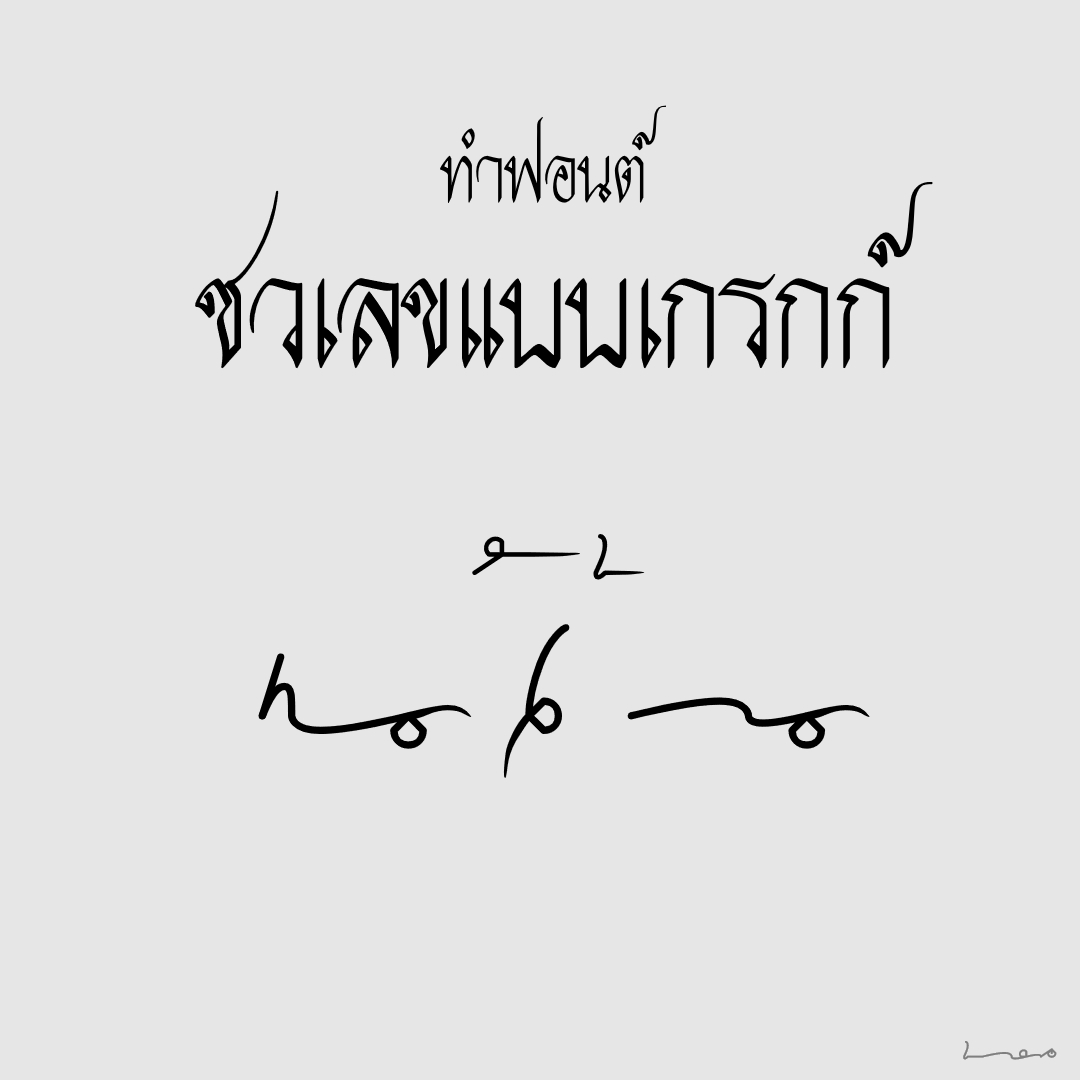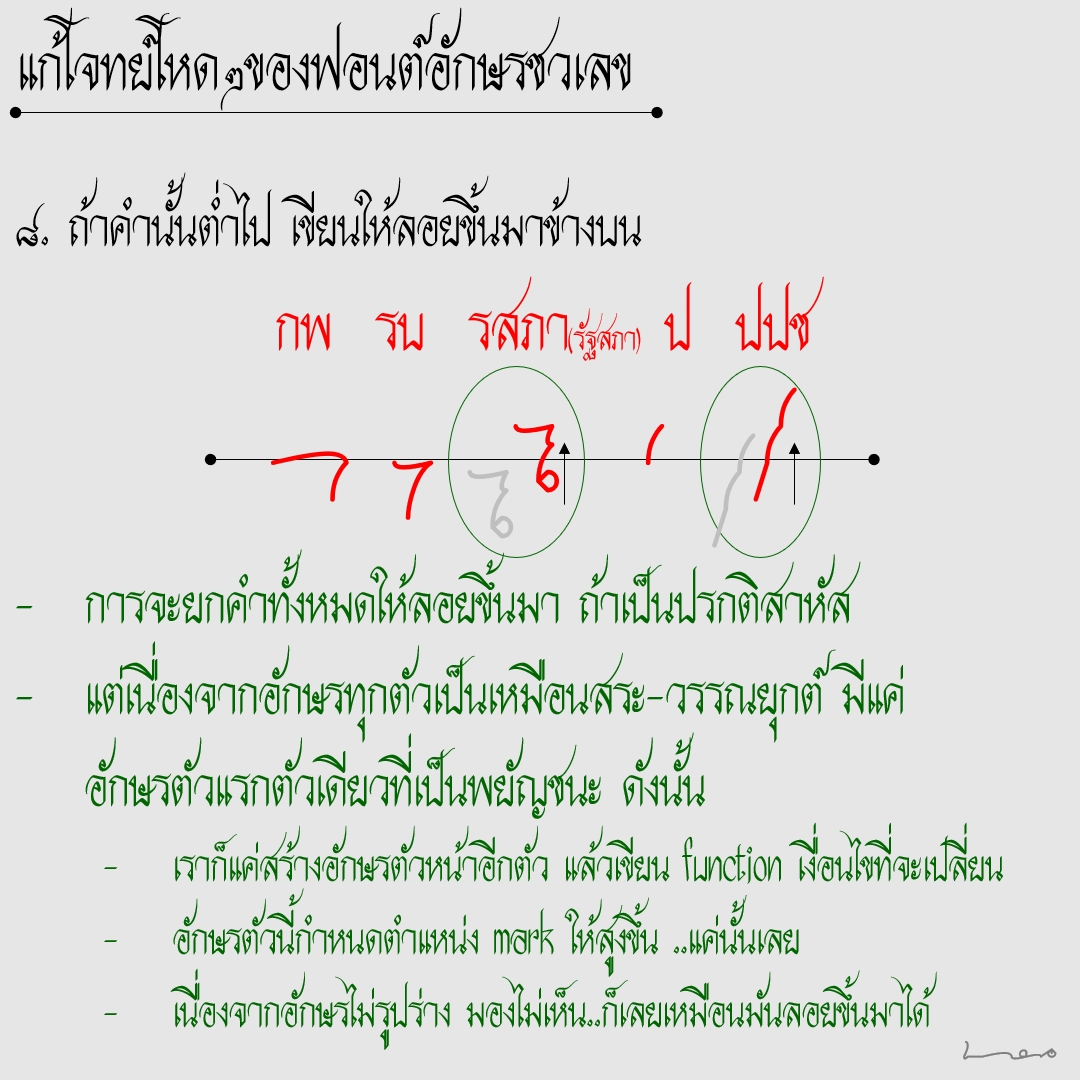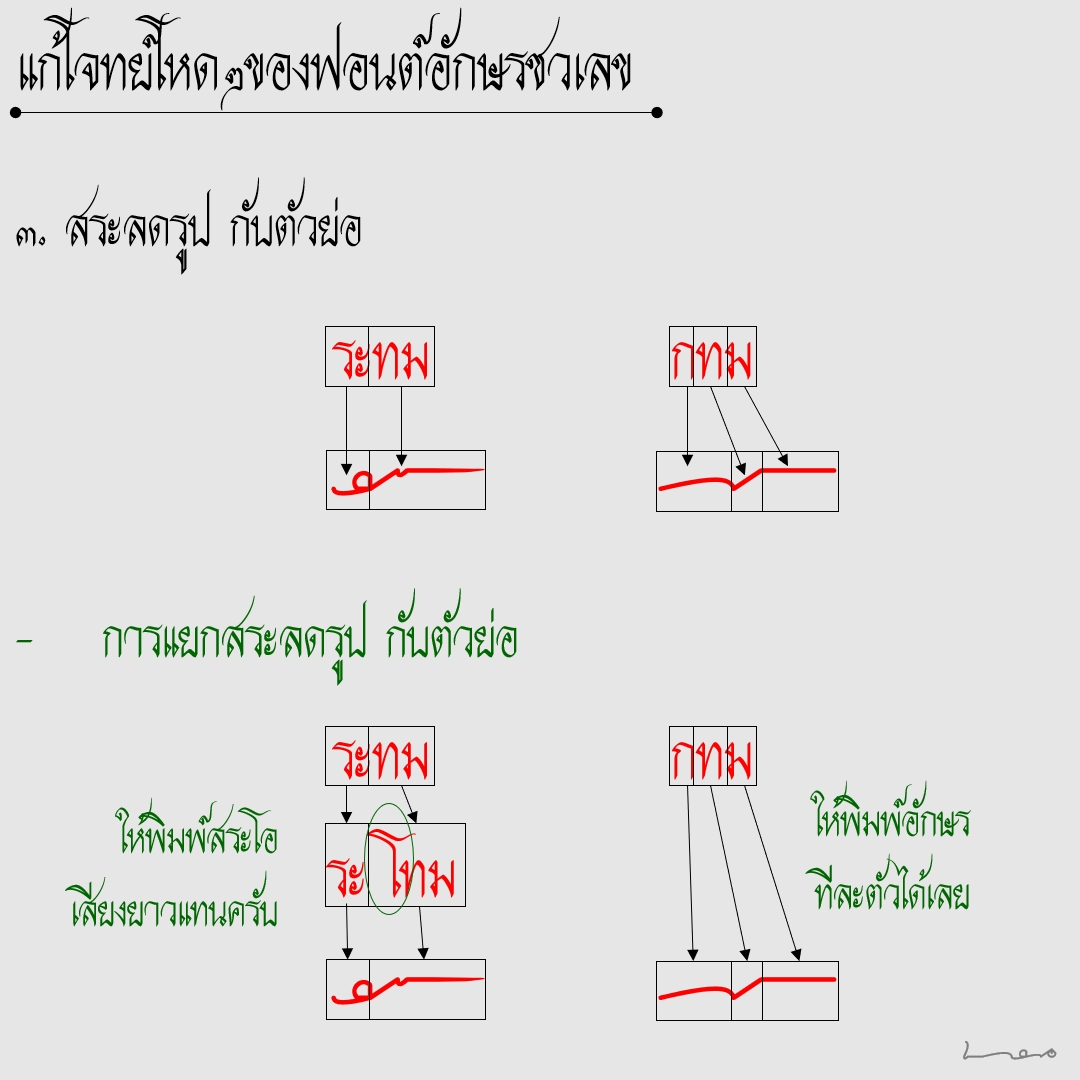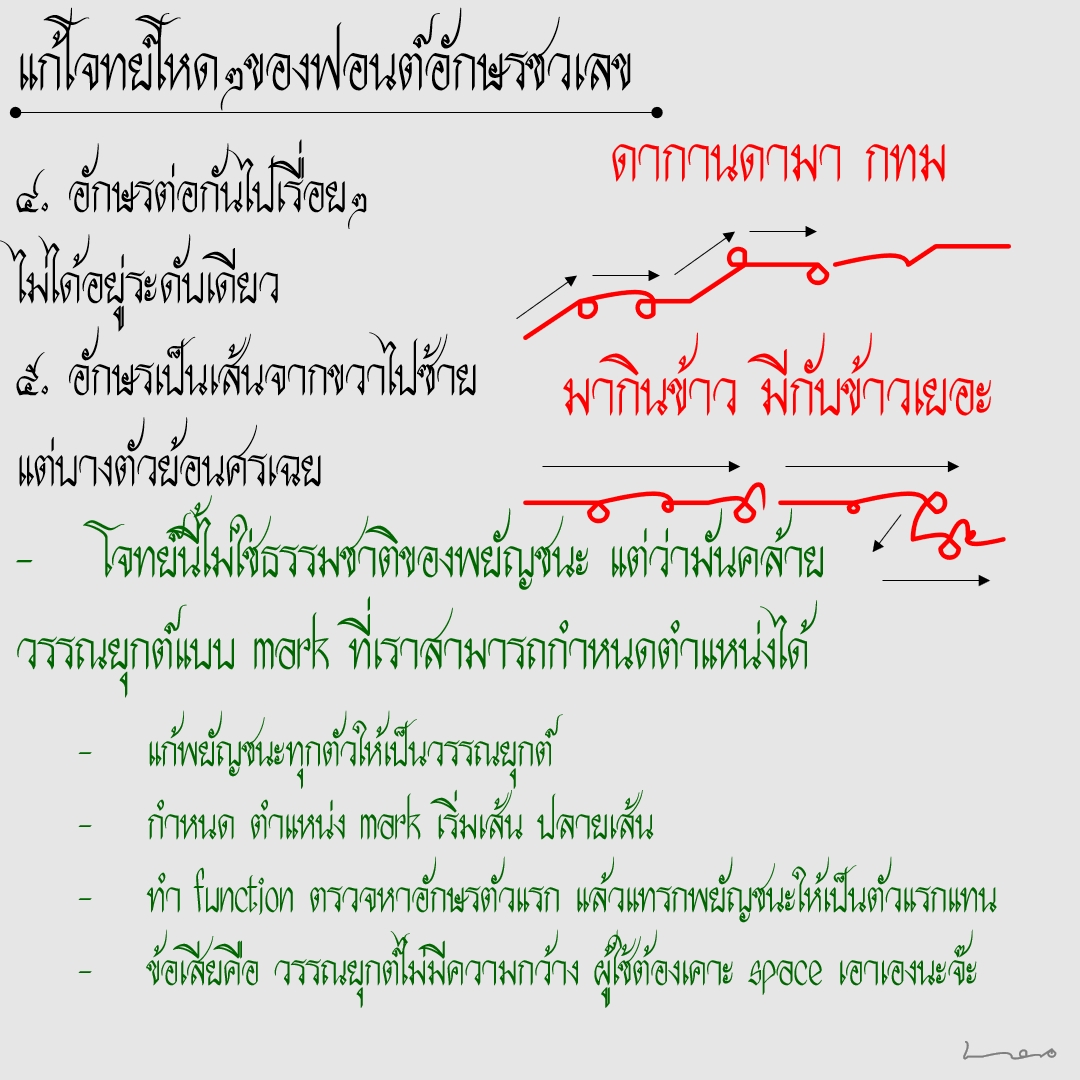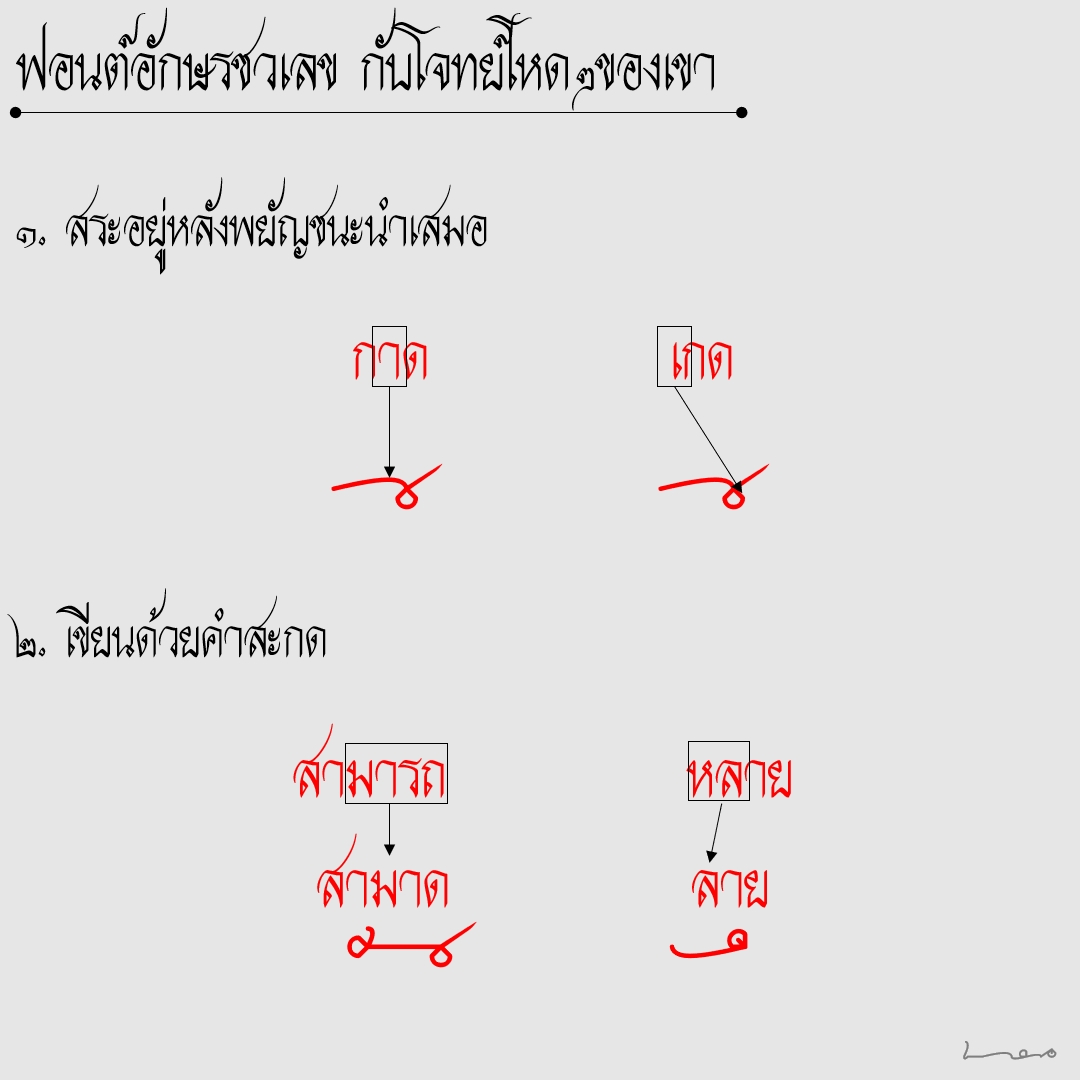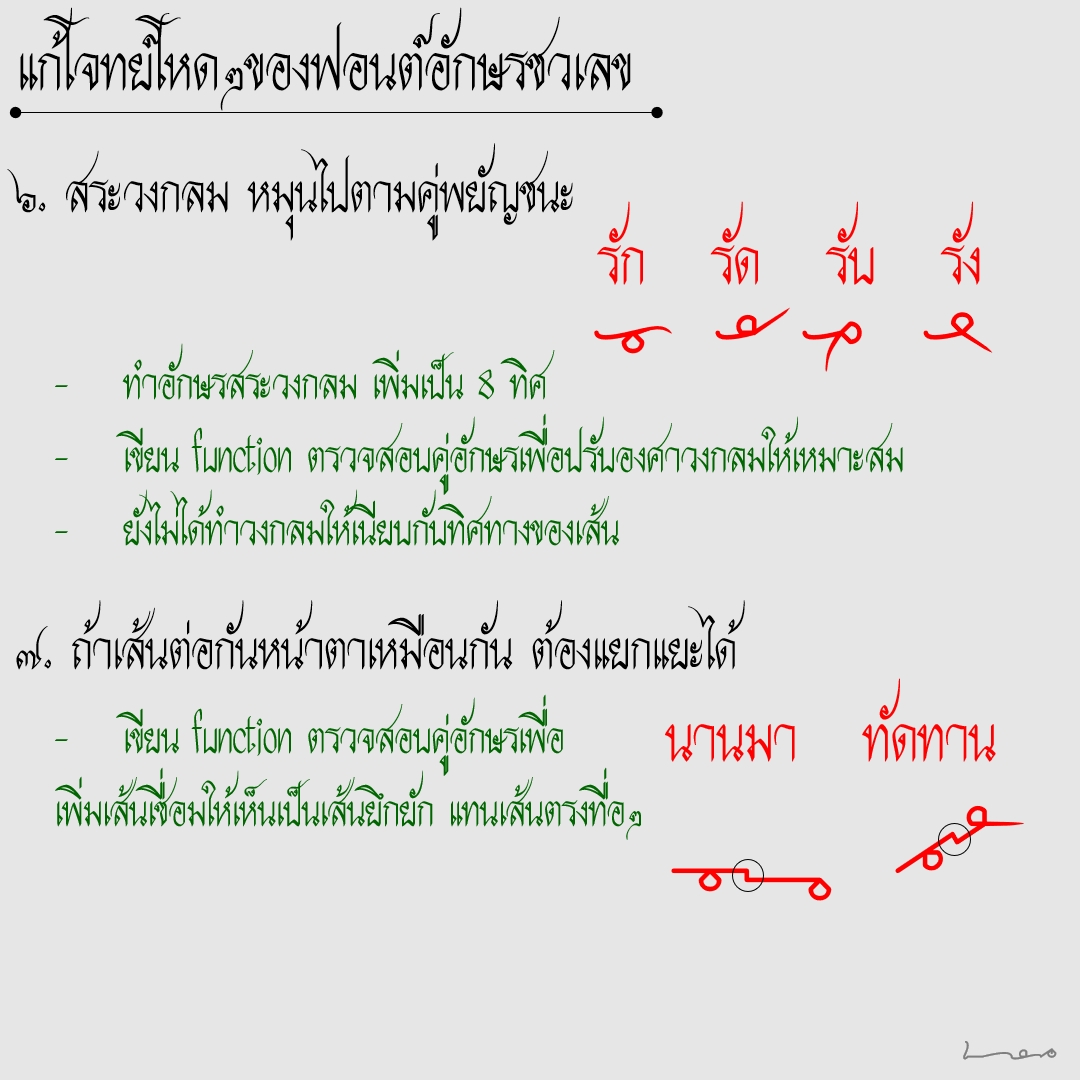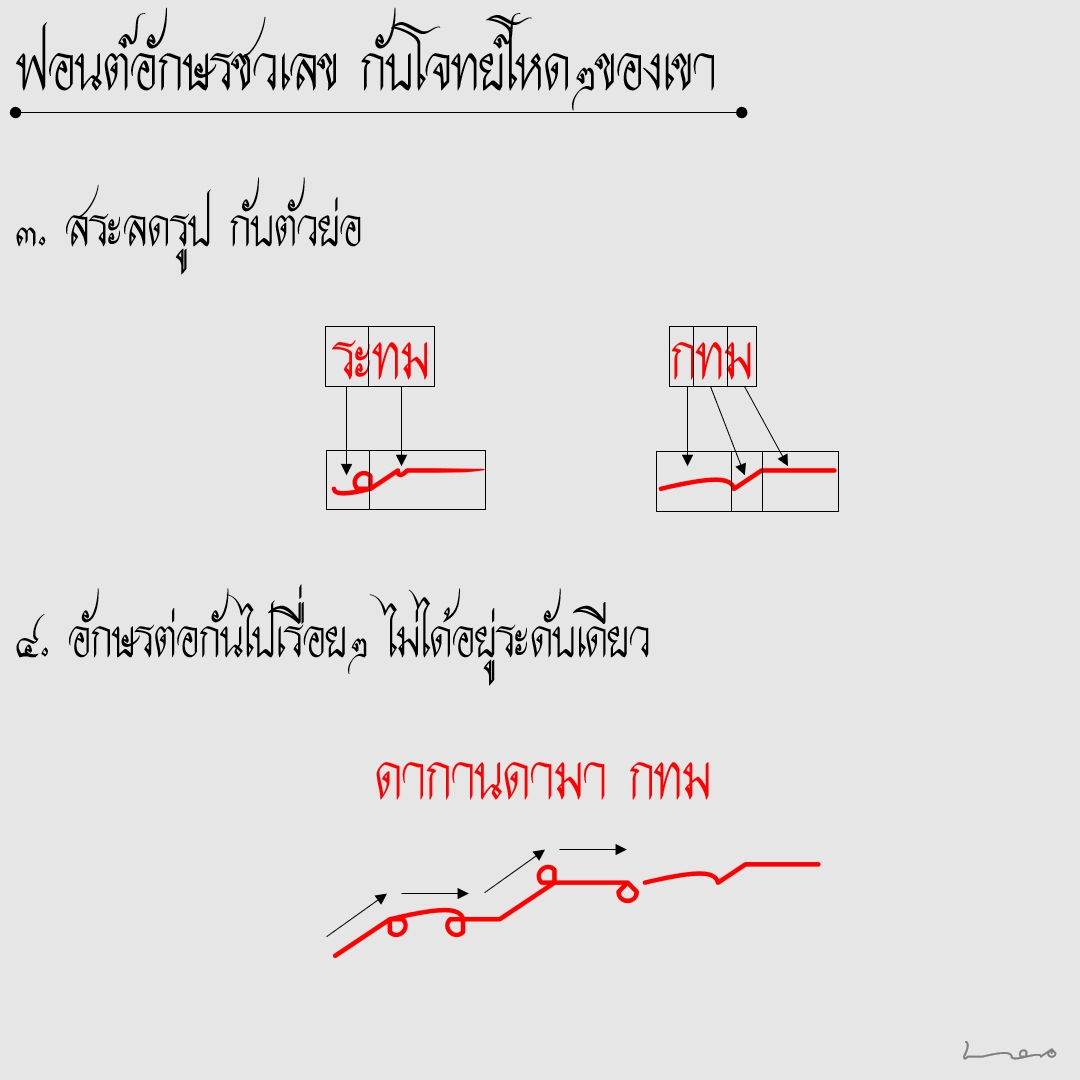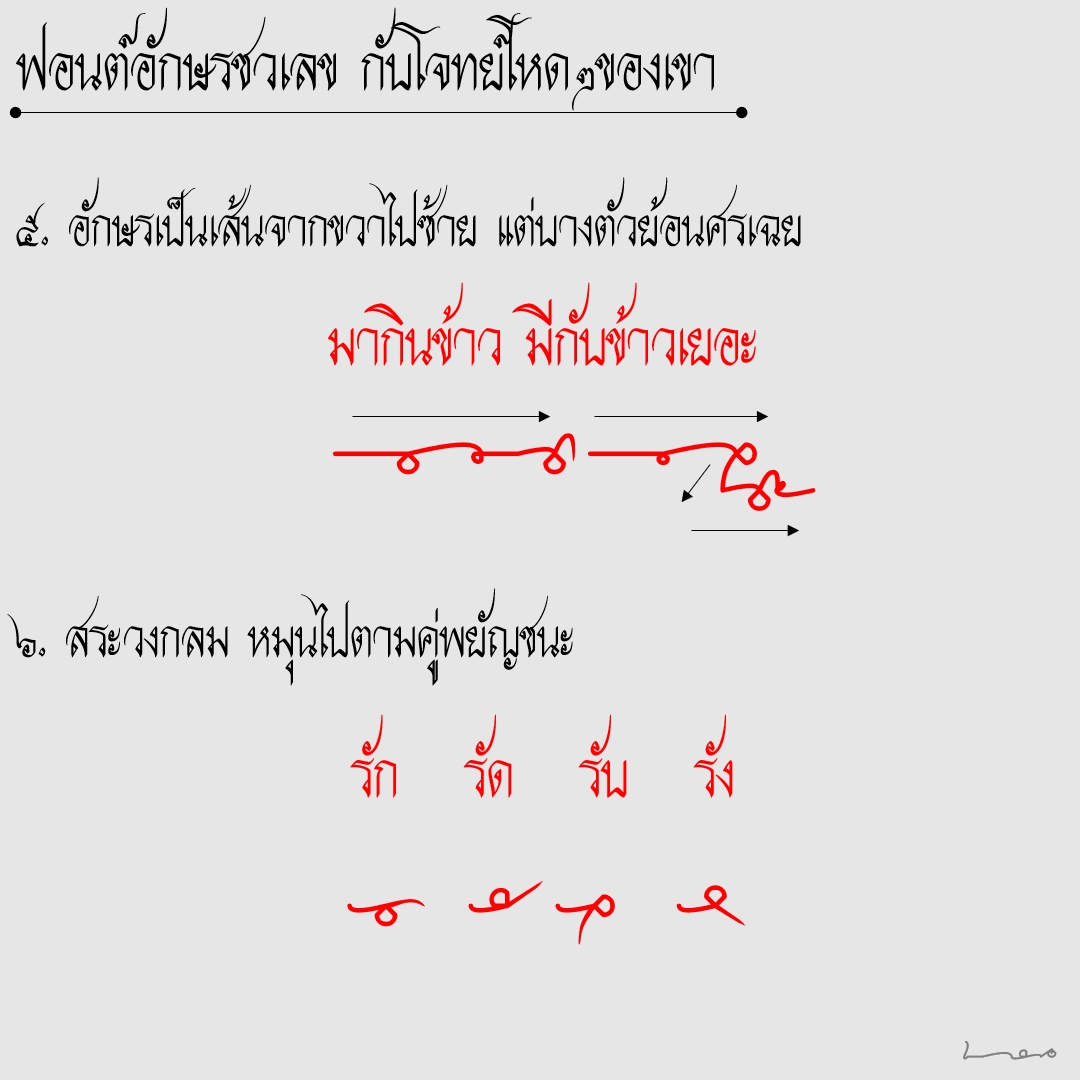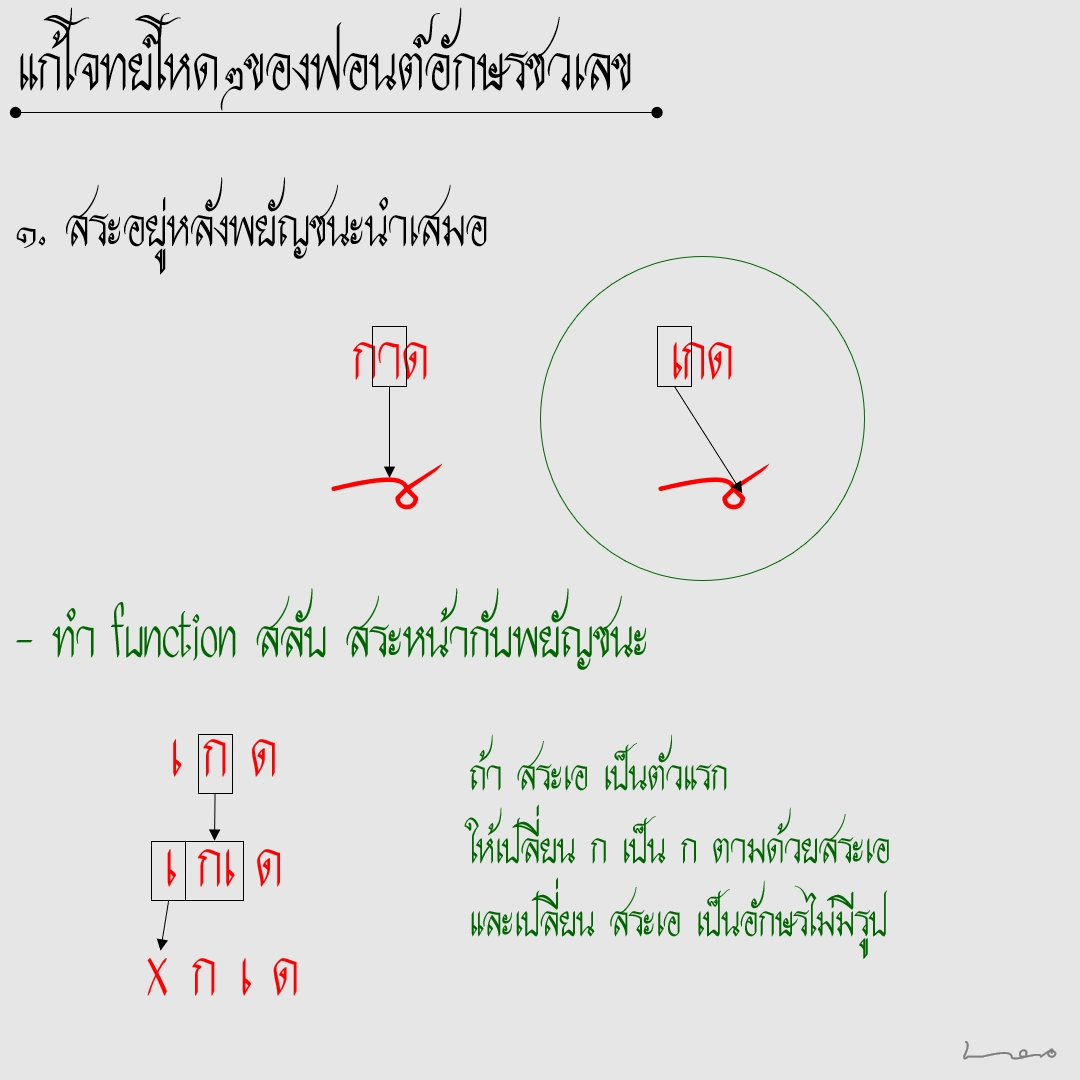
ทำฟอนต์ชวเลข
ถ้าใครสนใจจะทำอักษรชวเลข แบบเกรกก์ ตามนี้เลย..
ก่อนทำก็ชั่งใจหลายรอบ จะทำดีไหม เพราะมันไม่น่าใช้งาน.. ฟอนต์ชวเลข ไม่ได้ทำให้เร็วกว่าการพิมพ์ปรกติ ยิ่งปัจจุบันมี text2speed อยู่แล้ว ไม่ต้องมานั่งจดเอง ...แต่โจทย์มันยากดี
บทเรียนหลังจากทำเสร็จ
1. สำหรับตัวฟอนต์ ก็รู้สึกงั้นๆ ยังต้องปรับปรุงอีกเยอะ เพราะเว้นสิ่งที่ยังไม่ได้ทำไว้อีกเยอะ เช่นเรื่องจัดการวรรณยุกต์ เรื่องความสวยงาม
2. แต่เทคนิคที่ใช้แก้ปัญหาฟอนต์ตัวนี้ต่างหากที่น่าพอใจ สามารถเอาไปทำฟอนต์ที่เคยค้างคาไว้ได้อีก หลายตัวเลย ..จึงเข้าใจแล้วว่า ความสำคัญของงานวิจัย บางทีไม่ได้อยู่ที่ผลลัพธ์ของงานวิจัย แต่กระบวนการ เทคนิคต่างๆที่คิดค้นขึ้นมาแก้ปัญหาโจทย์ยากๆต่างหาก ที่สามารถเอามาต่อยอดได้อีกเยอะ